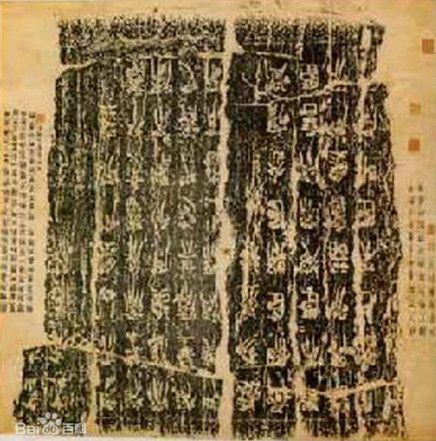
胡毋敬简介_毋字怎么读_书法作品欣赏_胡毋敬书法价值
在秦始皇统一规范文字的过程中,李斯将小篆的形体的开体与写法制定以后,为了推广到全国,李斯、赵高、胡毋敬等人以小篆编写书籍。在前面的文章中,我们简单地介绍了李斯书法和赵高书法的特点,本篇将对胡毋敬做一个简单地论述。
胡毋(wú)敬,又作胡母敬,姓胡毋,是中国秦朝人物,著名书法家,担任太史令。博识古今文字,与李斯、赵高共同省改大篆成为小篆书体,作《博学篇》。在创制小篆并使之规范化的工作中做出了一定的贡献。
秦朝时期,由丞相李斯编的《苍颉》,中书令赵高编的《爰历》,太史令胡毋敬编的《博学》,都是用法定的小篆字体编写的字书。这些字书同时教授字体和语法,也成为当时蒙童读书识字的标准版本。
胡毋敬书法
东汉许慎《说文解字序》云:“斯作《仓颉篇》。中车府令赵高作《爰历篇》。大史令胡毋敬作《博学篇》。皆取史籀大篆,或颇省改,所谓小篆也。”
胡毋敬秦汉书法
胡毋敬书法价值:
北魏王愔《古今文字志目》中卷列秦,汉,吴五十九人,中有胡毋敬。
唐张怀瓘《书断》卷中《妙品》亦谓胡毋敬“博识古今文字,亦与程邈、李斯省改大篆,著《博学篇》七章,覃思旧章,博采众训。”对创造小篆作出一定的贡献。作品无考。